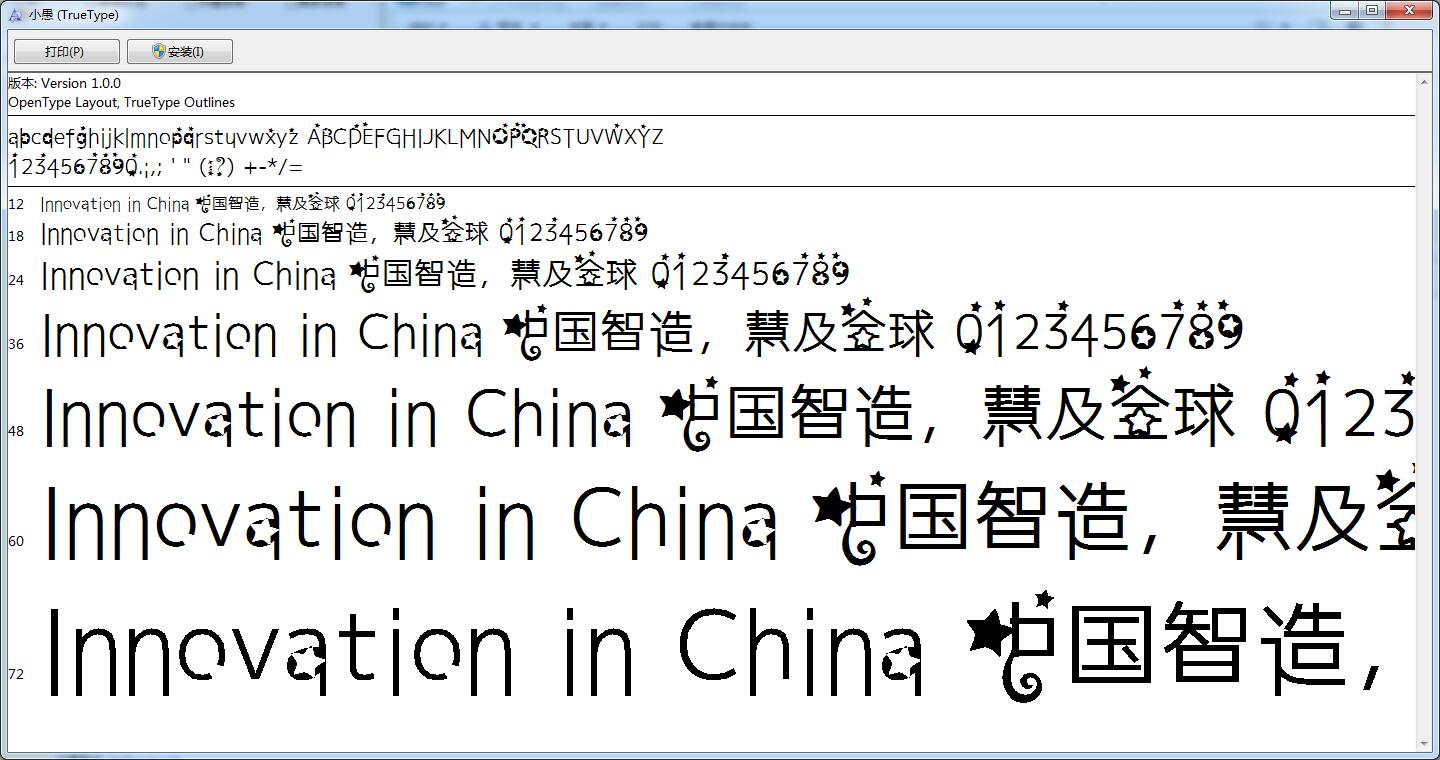
阿苗閃閃字體是一款比較有趣味的字體工具。該字體極具創(chuàng)意和藝術(shù)性,你可以在書寫婚禮邀請函、寫表白信的時候使用這款字體,可以將文字變得更加有創(chuàng)意哦!歡迎用戶來綠色資源網(wǎng)下載使用!
阿苗閃閃字體是是一款用于閃閃設(shè)計方面的字體應(yīng)用,這款字體以以黑體字體為原型所創(chuàng)作出的字體,在字體間加入啦星星圖案,使字體具有趣味性,該字體識別性強,整體風(fēng)格出色本作品適用于創(chuàng)意設(shè)計字體、藝術(shù)設(shè)計字體、星星設(shè)計字體!